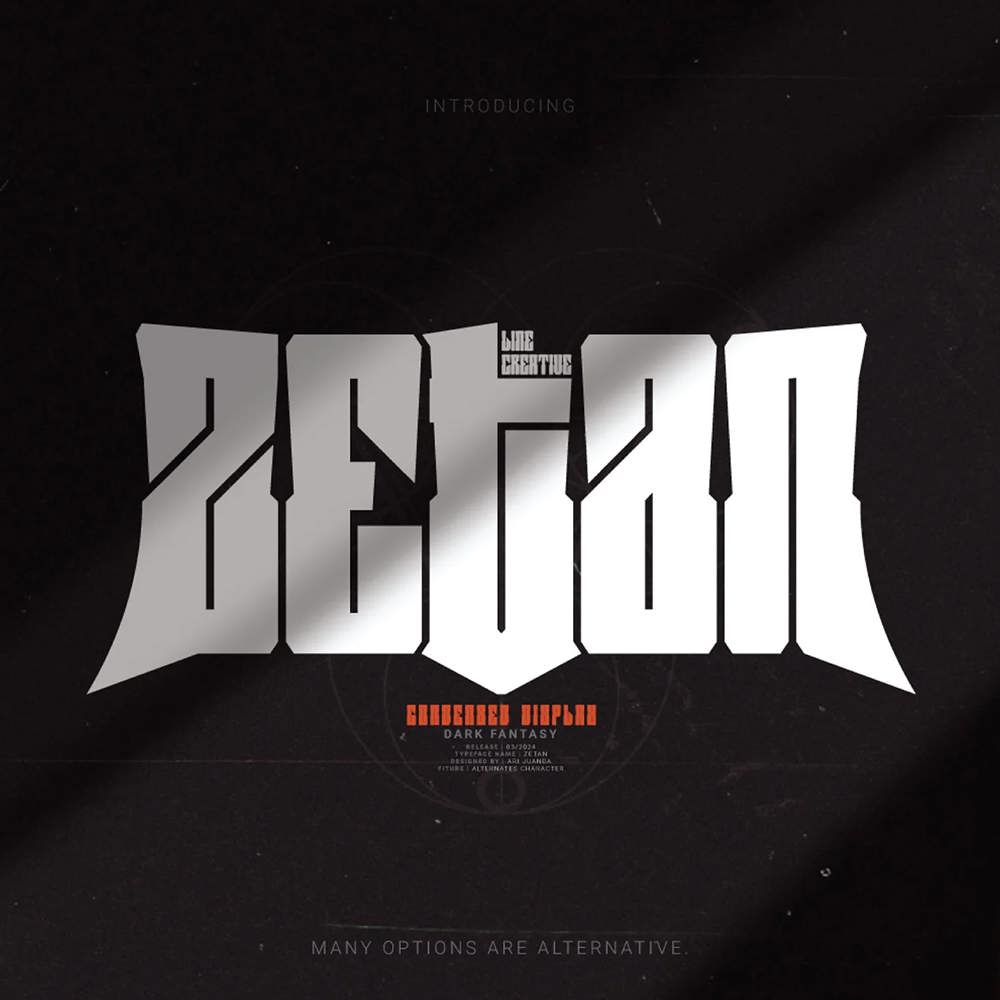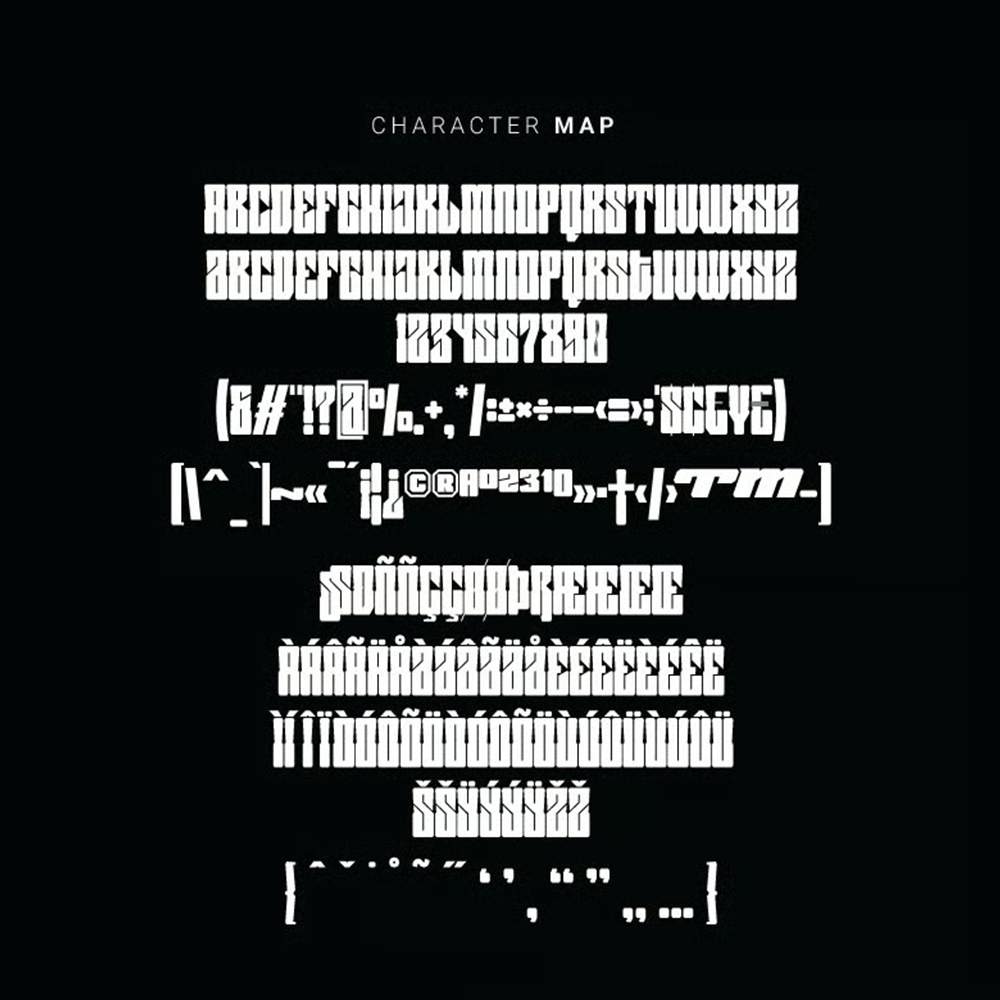
دانلود فونت انگلیسی Zetan Font
فونت پرمیوم و انگلیسی Zetan یک فونت قوی و جسورانه است که قدرت بروتالیسم را با زیباییشناسی مدرن دث متال ترکیب میکند. فونت Zetan شکلی محکم و استوار دارد و با کاراکترهای جایگزین ارائه میشود. وقتی این کاراکترها با هم ترکیب شوند، نوشتاری خشن، تیز و قدرتمند ایجاد میکنند.